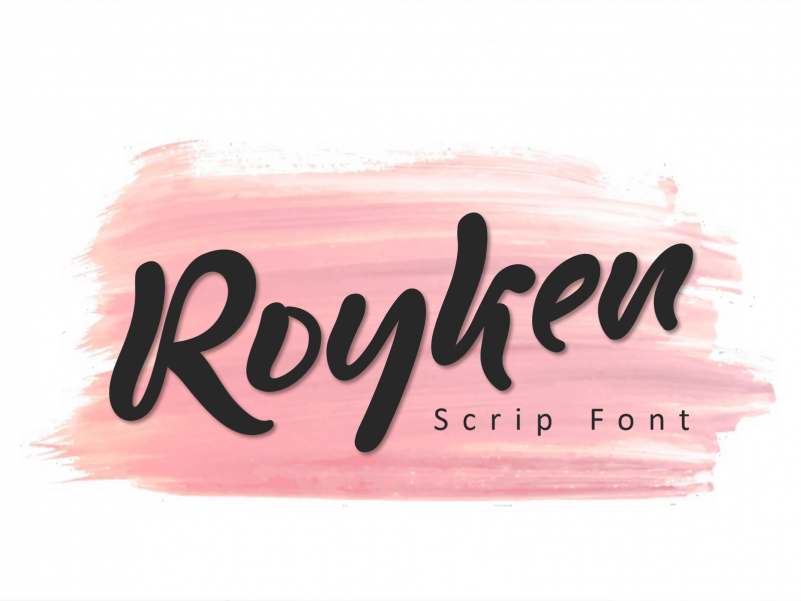
Royken Font – Fonte Grátis
Royken Font
A fonte Royken Font é uma criação poética e delicada do designer Nuryanto Dwi. Escrevendo-se com as mãos, essa fonte carrega consigo um toque de pureza, ideal para escrever cartões de aniversário ou convites de casamento, criando um ar romântico e pessoal que complementa qualquer design. Seja para personalizar uma invitacional bridal única ou criar uma identidade visual que expressa o amor em cada letra, Royken Font oferece a perfeita medida de charme e sutileza. Com sua aparência suavemente esculpida, essa fonte é tanto um recurso criativo quanto uma maneira maravilhosa de expressar sentimentos especiais por meio do design visual.